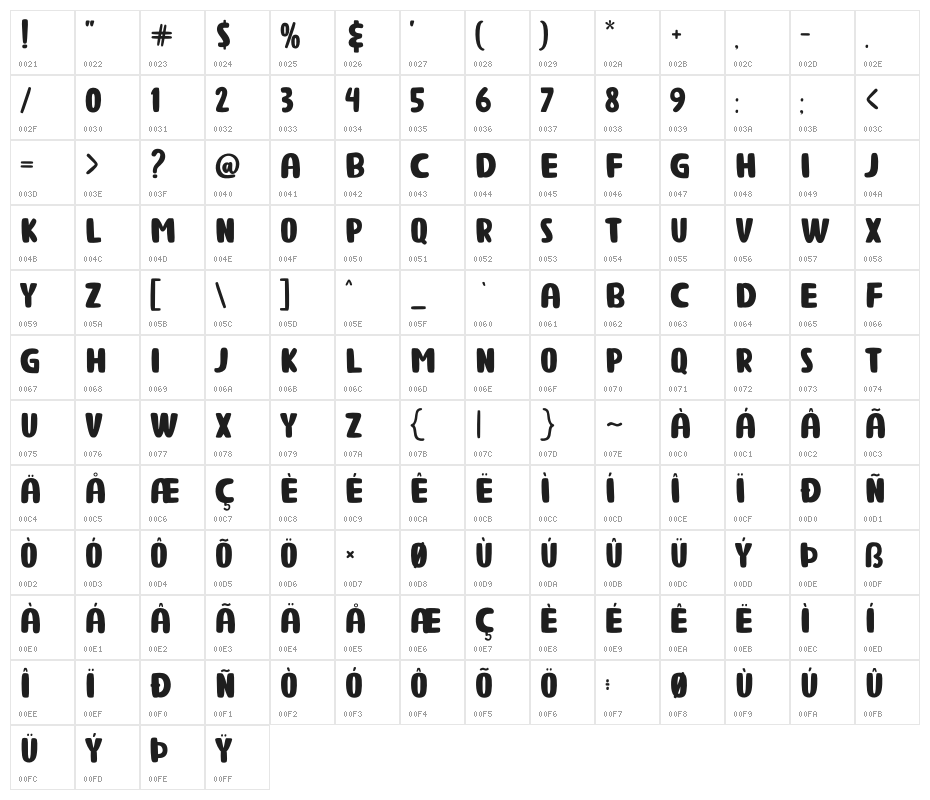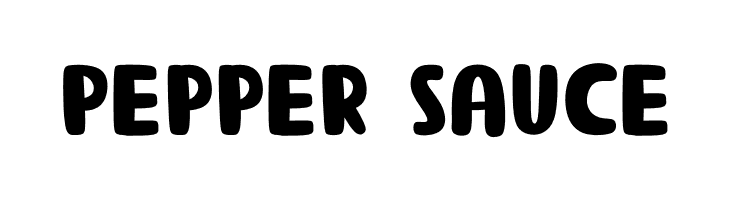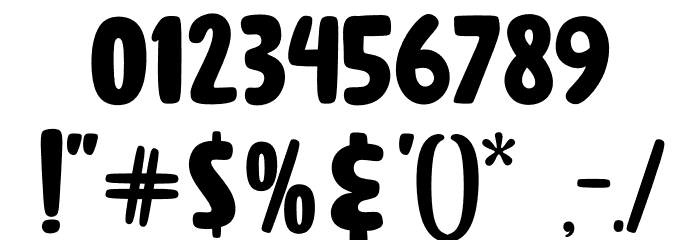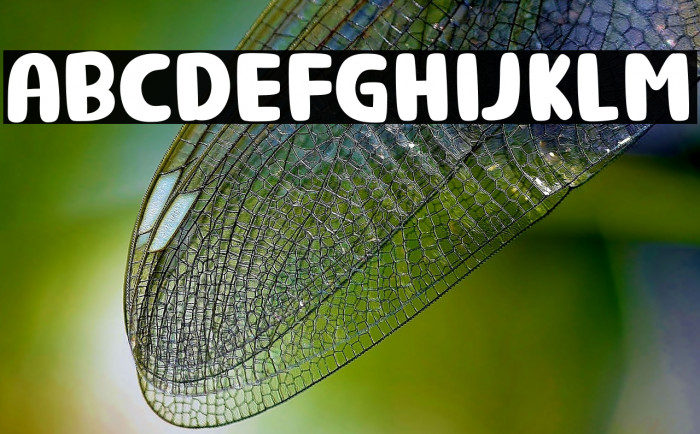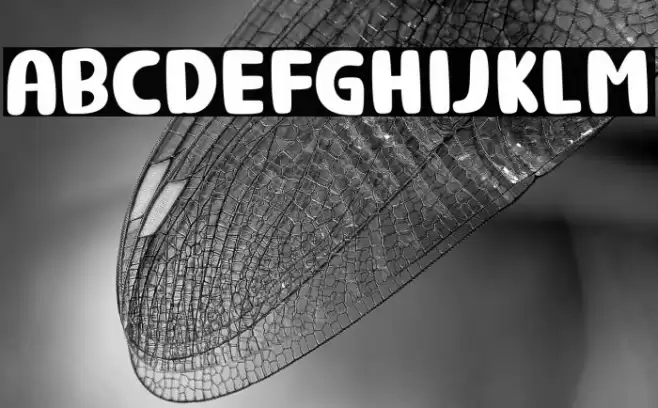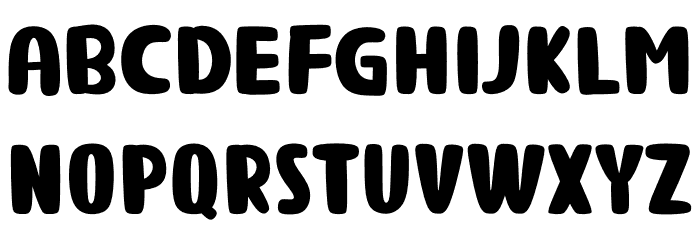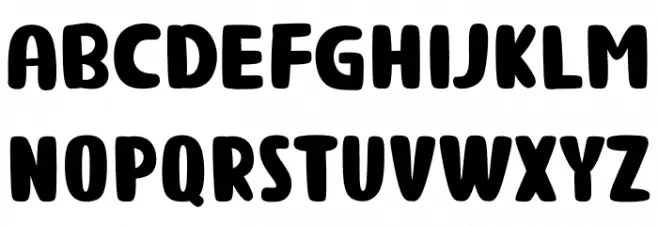
Pepper Sauce Font
✎ Comic
| श्रेणियाँ | Comic |
| समग्र शैली | Playful, Retro |
| उपयोग का मामला | Headlines, Logos, Posters |
| सुझाए गए प्रोजेक्ट | Ideal for children's books, playful branding, posters, and social media graphics. |